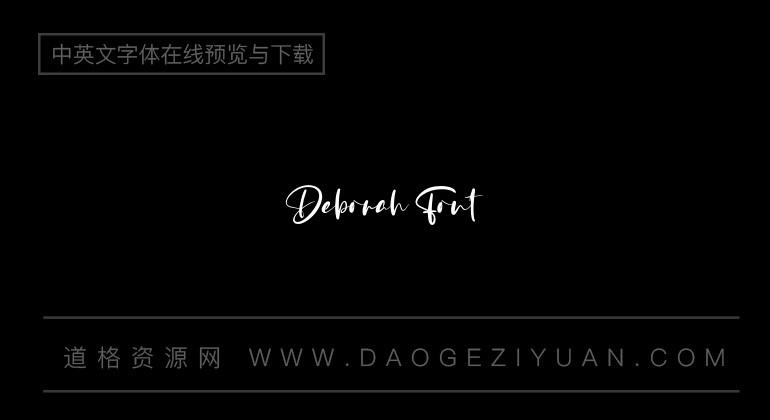
Deborah Font
Deborah Font 是一种非常流行的手写风格字体,常用于卡片、海报、标志和其他设计项目中。这种字体的特点是它非常自然,仿佛是由一支笔直接写出来的,给人一种温馨、亲近的感觉。它的线条流畅,笔画粗细不一,有一种独特的韵律感。Deborah Font 的字母形状和大小非常合理,易于阅读,同时也能够很好地与其他字体进行配合。总的来说,Deborah Font 是一种非常适合用于文本设计中的高质量手写风格字体。
Deborah Font是一款非常不错的手写艺术字体,具有很好的视觉感,适合于文化类的宣传设计、商业类品牌的广告和产品包装设计以及个性化文字排版等较多场景。